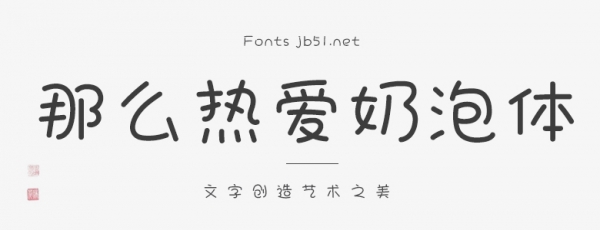
那么熱愛(ài)奶泡體,字體筆畫圓潤(rùn)活潑,弱化拐角,縮小筆畫對(duì)比,用圓形代替方形,整體趣味十足。每個(gè)字都是圓圓的活潑的可愛(ài)的,像是可愛(ài)少女甜甜的微笑,亦像是孩童呆萌的笑臉。適用于包裝設(shè)計(jì)、電商、品牌名稱、漫畫、影視綜藝、游戲、各類商業(yè)海報(bào)、戶外廣告標(biāo)題等設(shè)計(jì)領(lǐng)域,歡迎喜歡此字體的朋友前來(lái)下載使用。